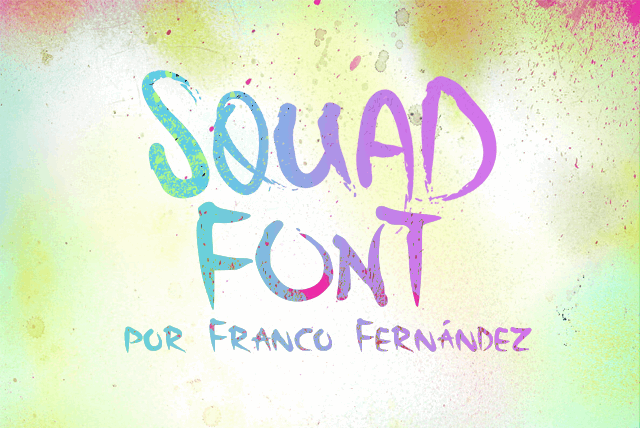
Squad Font – Fonte Grátis
Squad Font
A fonte Squad Font é uma deliciosa mistura de desenho alegre com sutileza elegante, perfeitamente adaptada para qualquer projeto que você esteja planejando. Inspirada no universo explosivo do filme “Suicide Squad”, essa brush font oferece uma textura única e vibrante capaz de destacar seu design em qualquer layout. Ideal tanto para criar um design gráfico arrojado quanto para dar um toque memorável a qualquer projeto de marca, a Squad Font é o elemento perfeito para dar vida aos teus projetos digitais. Além disso, foi criada pelo talentoso designer Franco Fernández, que adicionou uma sensação única e vibrante à fonte através da sua arte de brush. Seja você um entusiasta do design ou apenas alguém procurando por aquela fonte perfeita para seu próximo projeto de design, a Squad Font é definitivamente algo que não pode ser deixado passar despercebido.